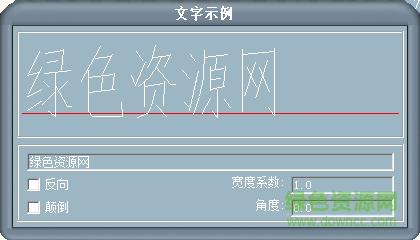
cad gb07.shx字體是一款常常用于auto CAD軟件的大字體,打開(kāi)圖紙就能很方便的看到很清楚,可支持制圖軟件中圖紙文字的顯示,大家按照以下步驟安裝該字體就可以使用了,有需要者快來(lái)下載使用吧!
亞洲字母表包含數(shù)千個(gè)非 ASCII 字符。為支持這種文字,程序提供了一種稱作大字體文件的特殊類(lèi)型的形定義。用戶可以將樣式設(shè)置為同時(shí)使用常規(guī)文件和大字體文件。